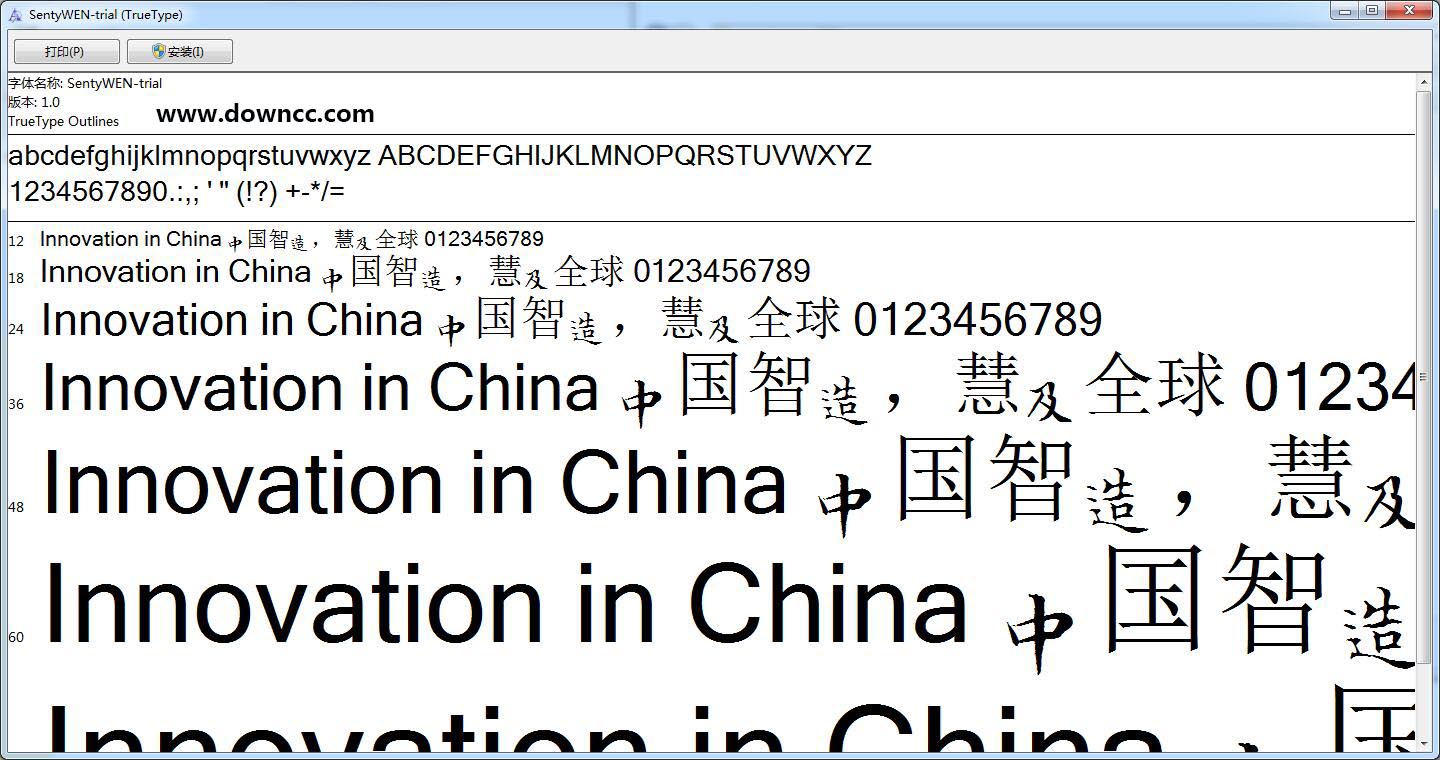
新蒂文徵明體專業(yè)版
新蒂文徵明體字體專業(yè)版算是新蒂字體系列中的最秀美的一款字體了。利用它輸出的文字看起來非常雋秀清新,多倍應(yīng)用于排版設(shè)計(jì)方面使用!需要的用戶可以來綠色資源網(wǎng)下載!
新蒂文徵明體字體是一款比較規(guī)范的手寫字體,活化中國古代碑帖書法字體,適用于繁體中文的一種字體,字體雋秀,清麗。新蒂文徵明體與其他新蒂字體一樣都很有特色,適合用于平面或者圖片文字logo處理,廣泛應(yīng)用于書法設(shè)計(jì)、廣告平面設(shè)計(jì)等行業(yè)!